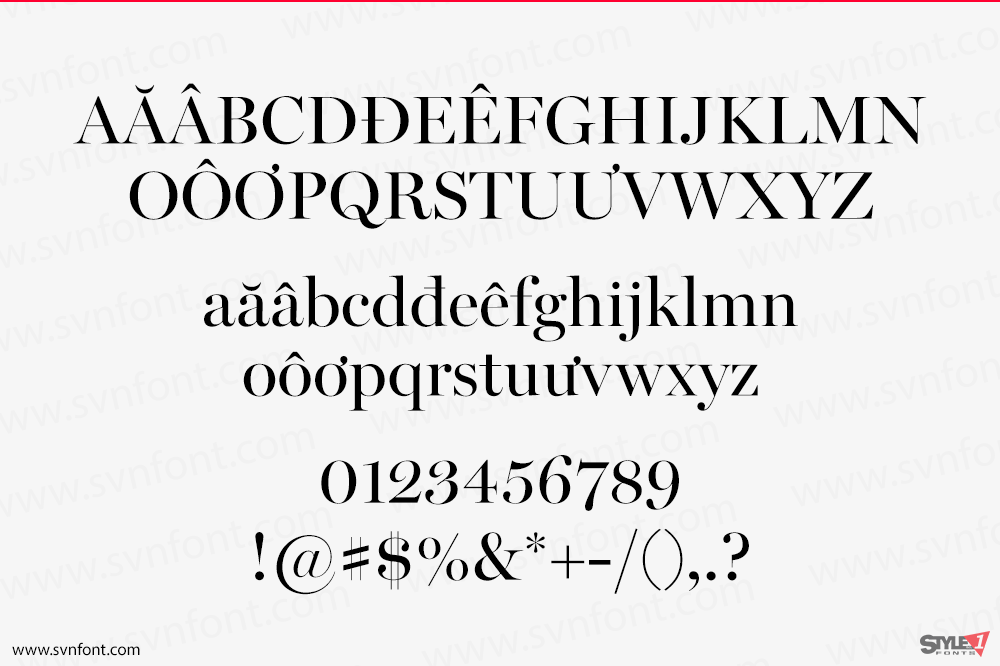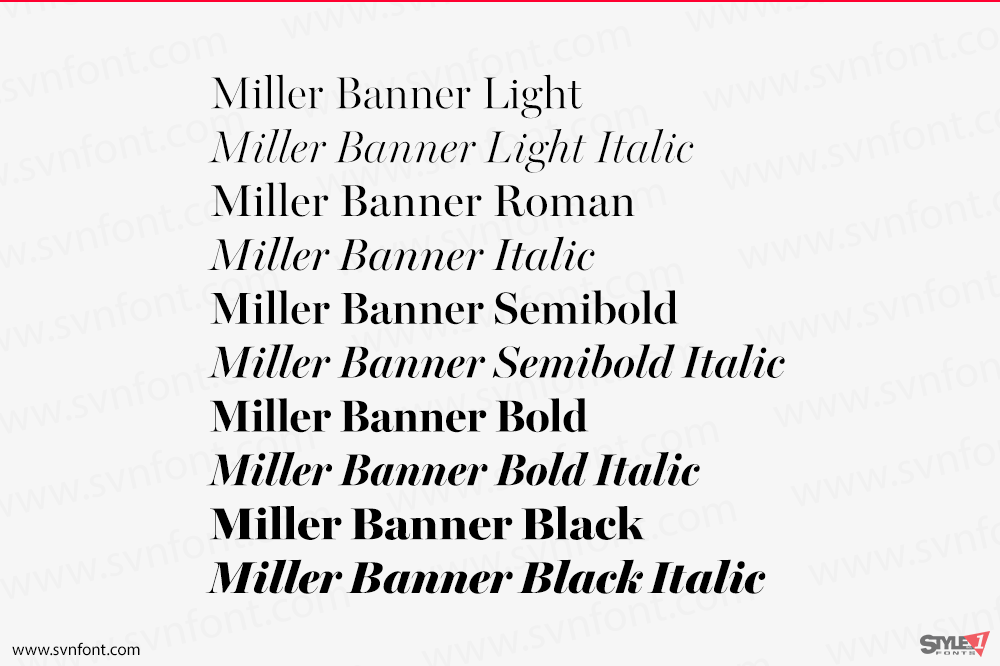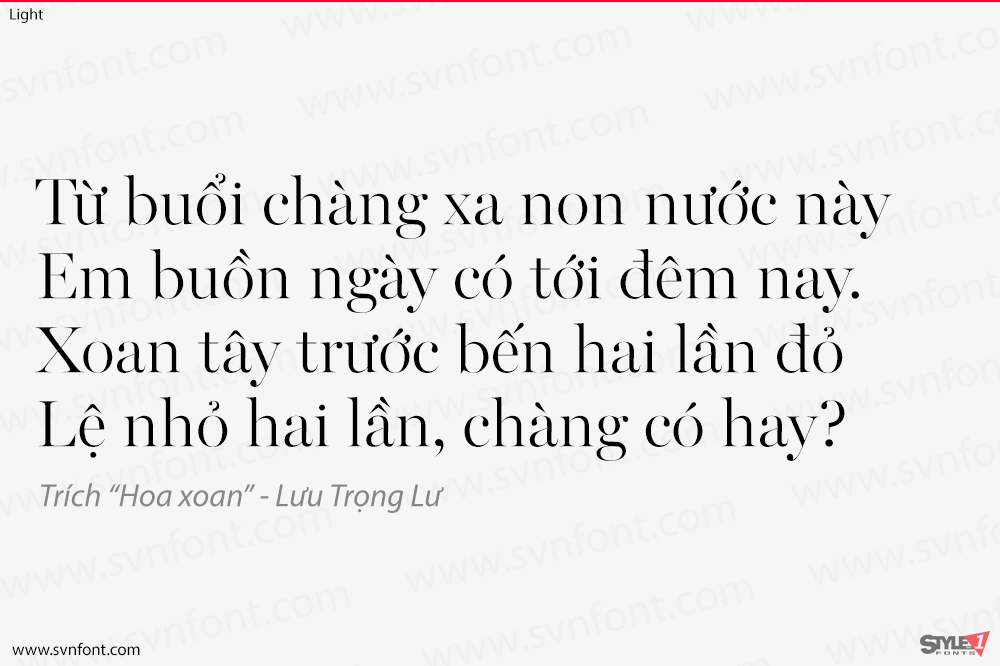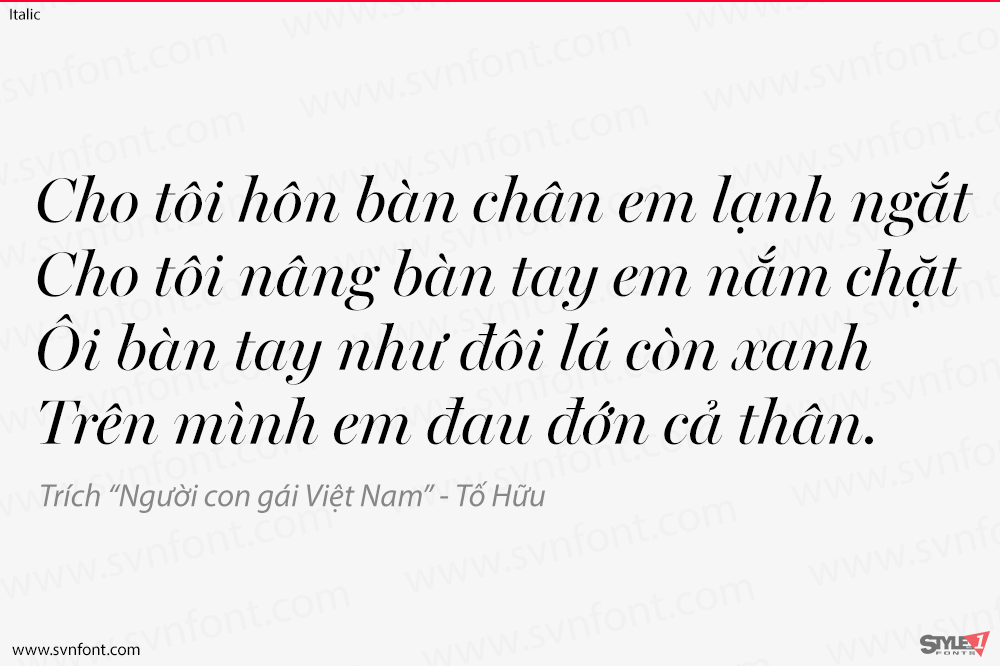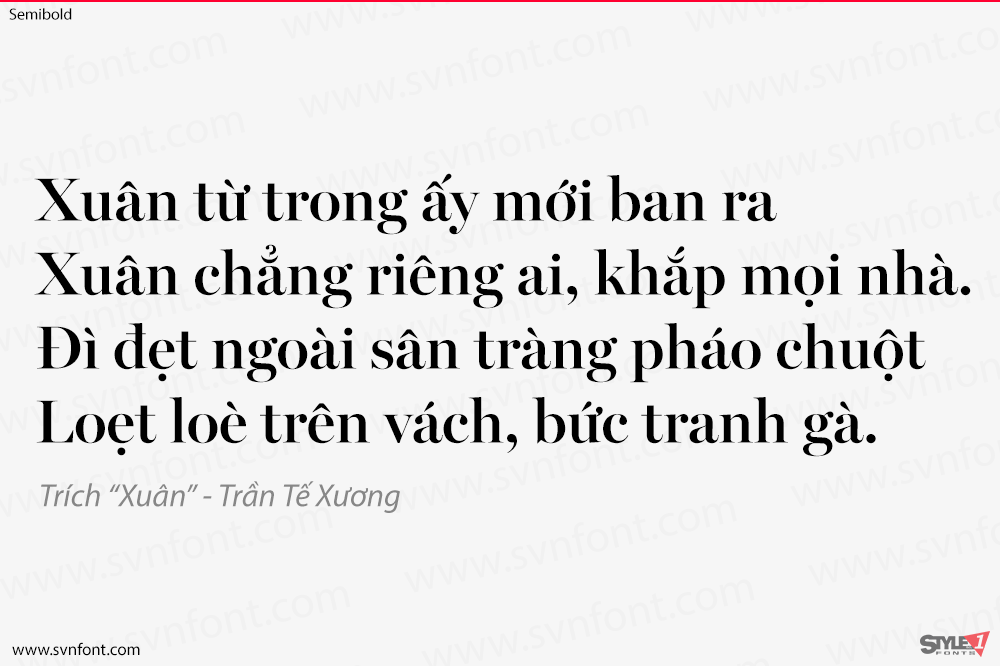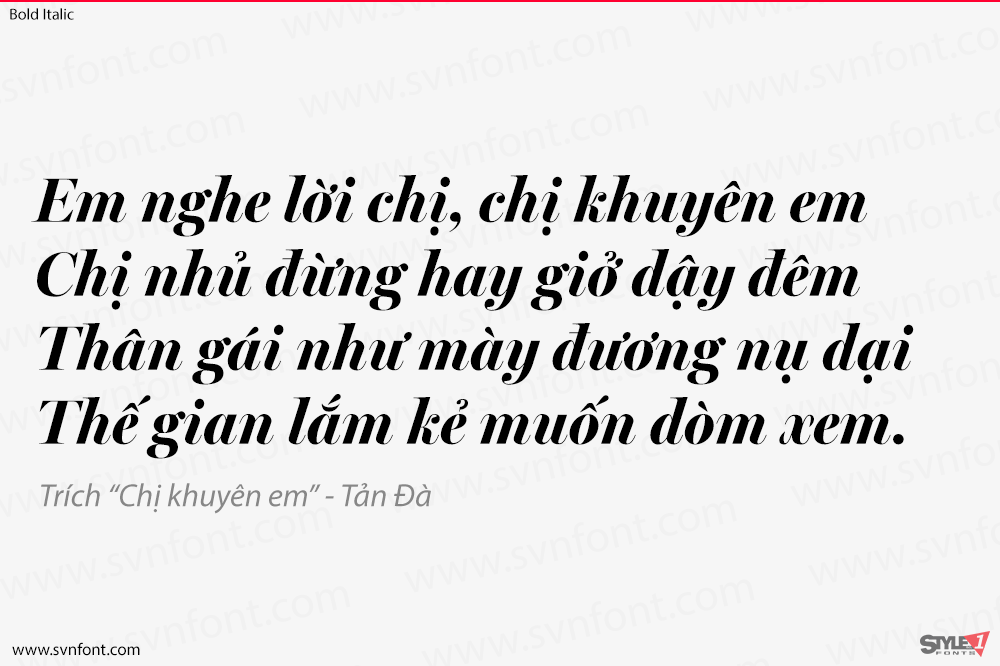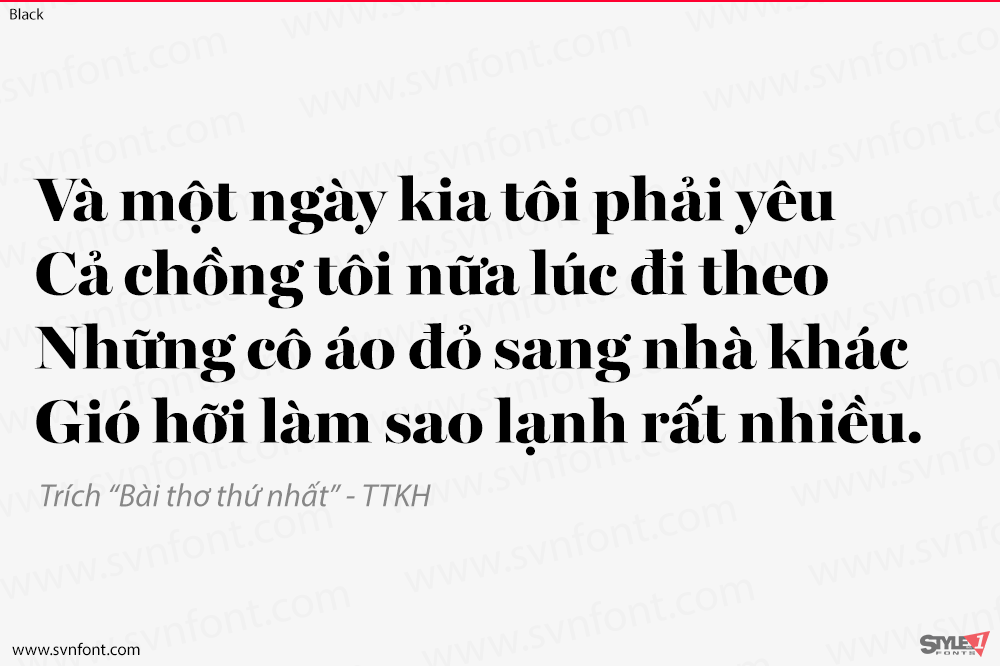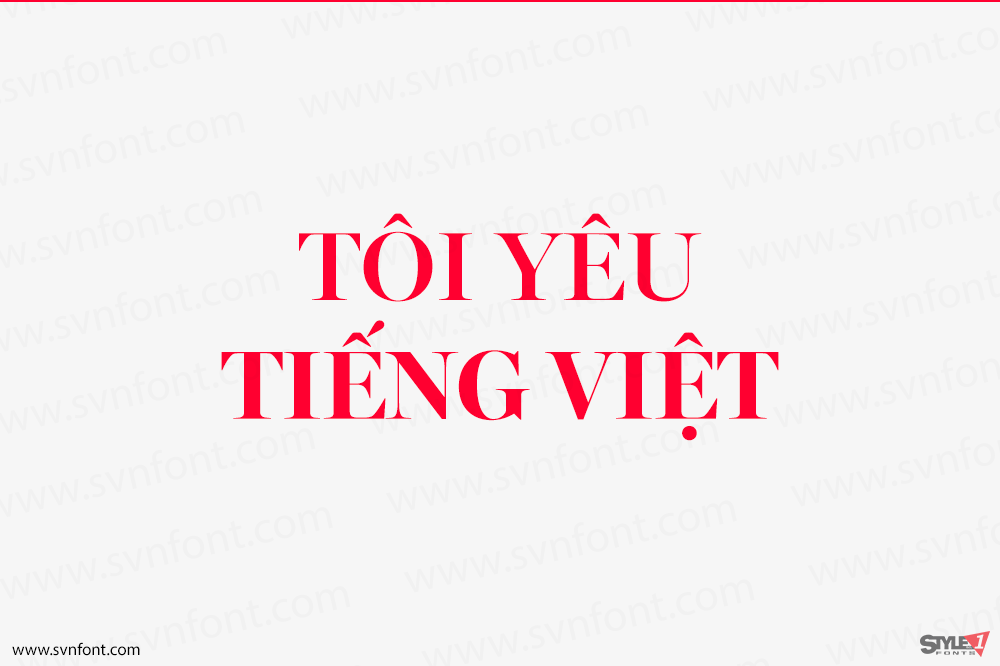
Miller Banner nâng dòng phông chữ Miller nổi tiếng của Matthew Carter lên một tầm cao mới: từ 100 điểm ảnh trở lên, vượt xa bất kỳ ví dụ nào trong các kiểu chữ Scotch Roman lịch sử trước đây. Được tối ưu hóa cho các cài đặt rất lớn, những đường mảnh đã được làm sắc nét hơn và độ tương phản được làm ngọt hơn, mang lại vẻ duyên dáng và thanh lịch sắc nét cho các tiêu đề và tựa đề lớn. Richard Lipton đã chuẩn bị các kiểu chữ này, bổ sung thêm một độ đậm Black mới đầy quyến rũ cho tạp chí Glamour. Trong số các công dụng khác, Miller Banner được khuyến nghị sử dụng cho Báo và Tạp chí.
Nhà thiết kế: Matthew Carter & Richard Lipton
Nhà phát hành: Font Bureau